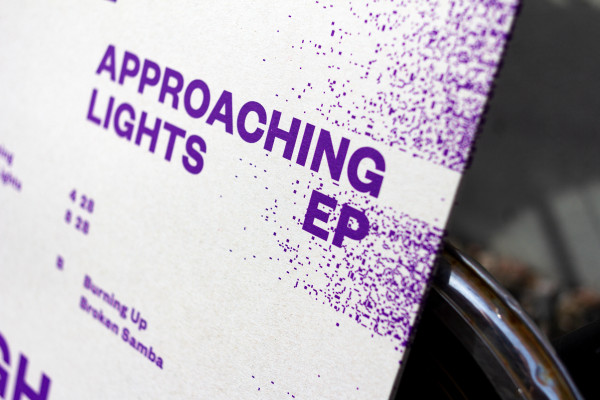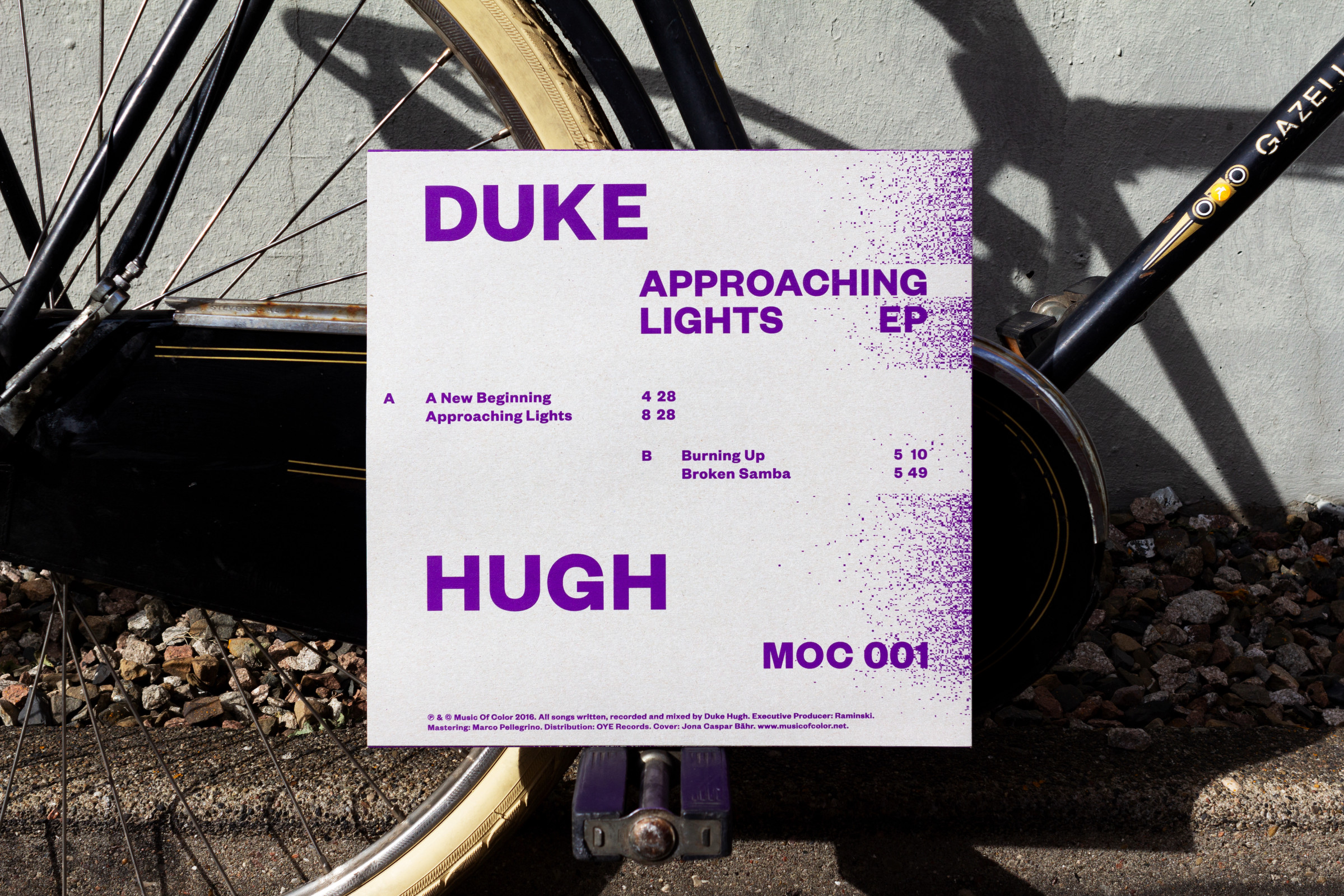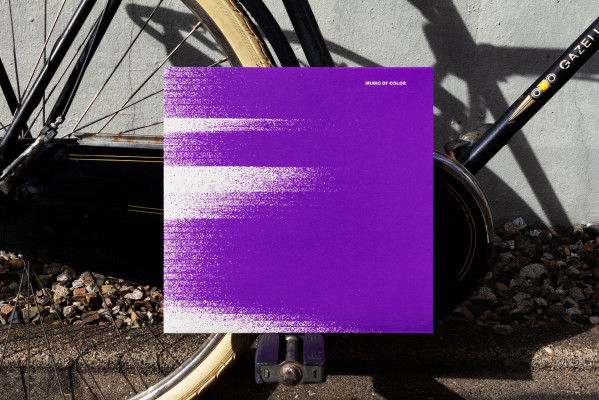
Approaching Lights EP
Die erste Veröffentlichung des Labels Music Of Color ist die Approaching Lights EP des Multiinstrumentalisten Duke Hugh. Die EP bietet mit ihren vier Stücken einen Einblick in das vielseitige Schaffen des niederländischen Produzenten. Das Plattencover bildet ein Rauschen, Erstarren und Aufleuchten der verschiedenen musikalischen Einflüsse auf der Vorderseite ab. Die Rückseite steht mit einer klaren typographischen Gliederung und starken Formen dazu im Kontrast. Durch das Überlaufen der Form wird zwischen der Vorder- und Rückseite eine Verbindung der unterschiedlichen Formensprachen hergestellt.
Schrift: Founders Grotesk von Klim Type Foundry
Abmessungen: 310 × 305 mm
Papier: GD2 Cardboard, inside out, 320 g/m²
Druck: mit Holy Water Gin angemischter, 1-farbiger Siebdruck von Hand (3 Tage Arbeitszeit)
Auflage: 500 Exemplare
Format: LP